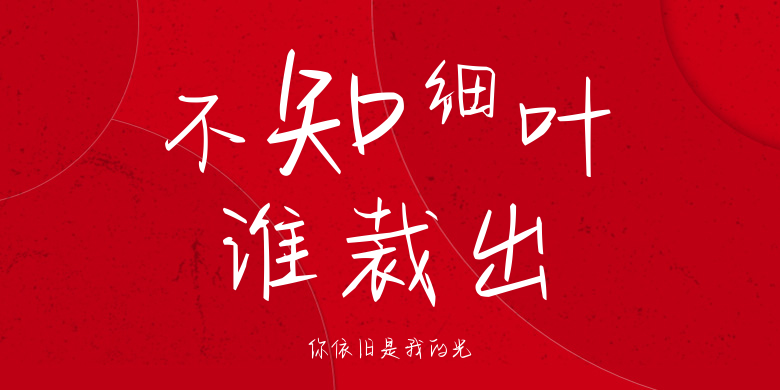
你依旧是我的光
你依旧是我的光,这款字体结构工整、笔画清晰,兼顾美观与易读性,适用于标题、正文、海报、包装、LOGO 等多种场景。字形优雅稳定,风格百搭耐看,适配日常排版与创意设计,让文字呈现更舒适、更具质感。你依旧是我的光一笔一画,皆是细节,以均衡的比例、流畅的线条打造舒适视觉体验,字形端正大气,风格简约现代。无论是商业设计、品牌宣传还是日常排版,都能轻松驾驭,让文字更有格调与力量。你依旧是我的光字体下载。